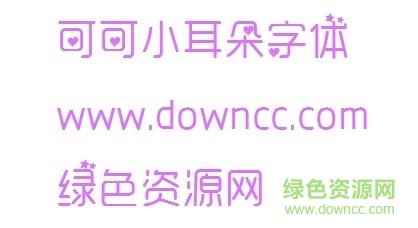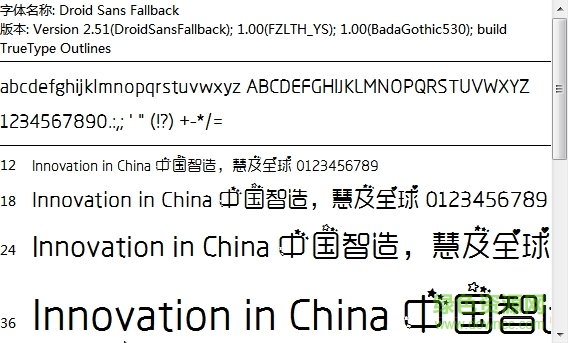
可可小耳朵是一款超級(jí)蘇萌的卡通字體,不僅有著可愛(ài)星型和桃心圖案,對(duì)部分漢字也做出了有特色的鏤空處理,十分悅目,快來(lái)綠色資源網(wǎng)下載收藏吧!
可可小耳朵是一款用于非主流設(shè)計(jì)方面的字體,給文字更加特色趣味的裝飾和點(diǎn)綴,可用于廣告設(shè)計(jì)字體、網(wǎng)頁(yè)設(shè)計(jì)字體、包裝設(shè)計(jì)字體、 屏幕顯示字體等。
可可小耳朵字體能滿(mǎn)足廣大用戶(hù)的童真童趣和少女心,超Q萌的點(diǎn)綴圖案讓文字更加生動(dòng),讓內(nèi)容更容易吸引大家的眼光。